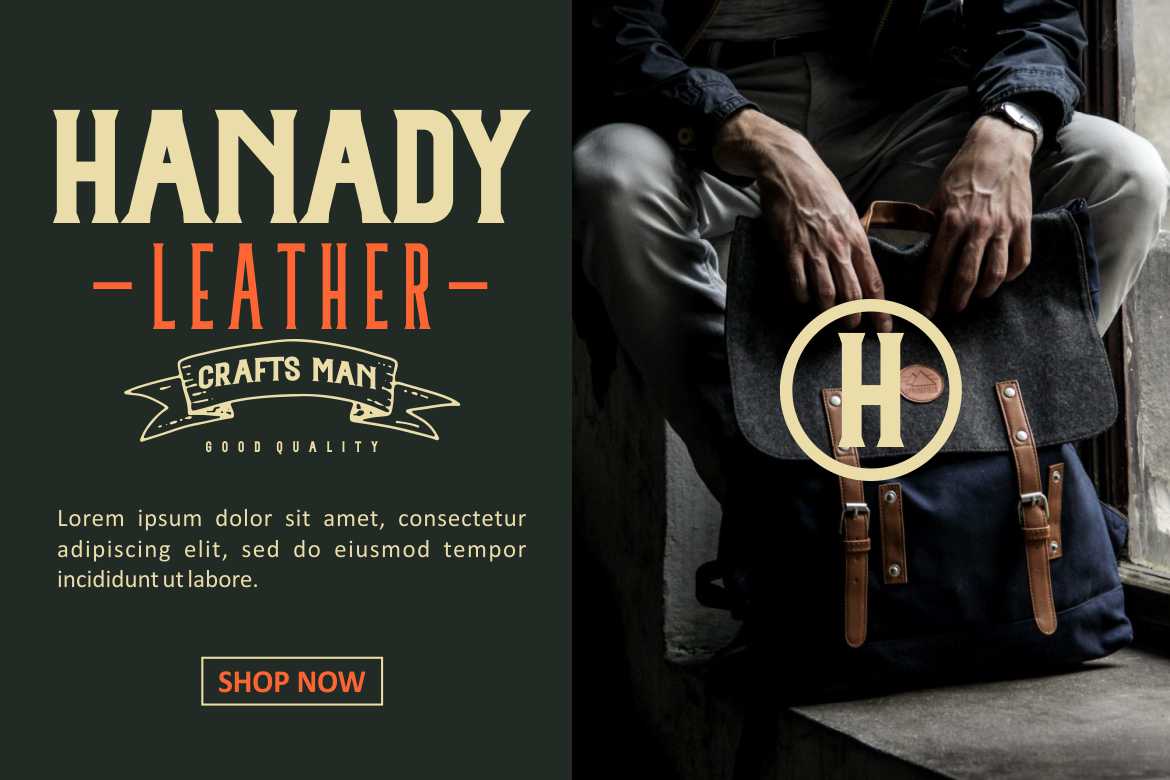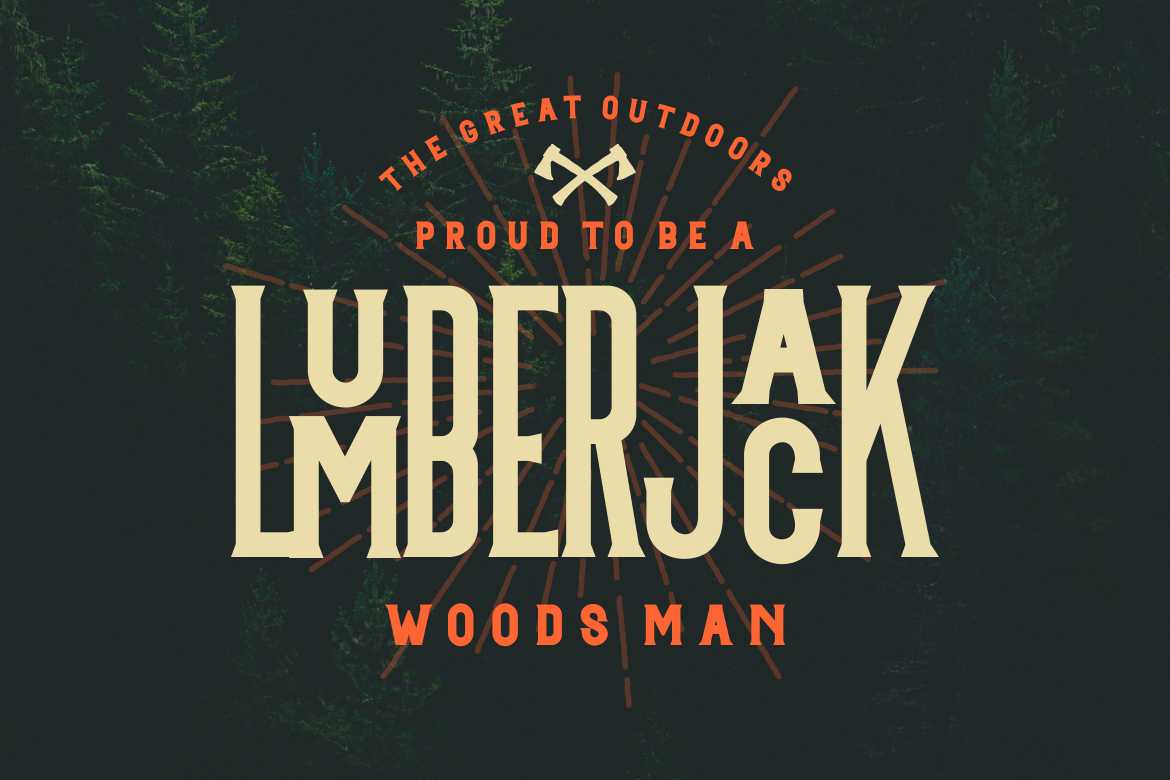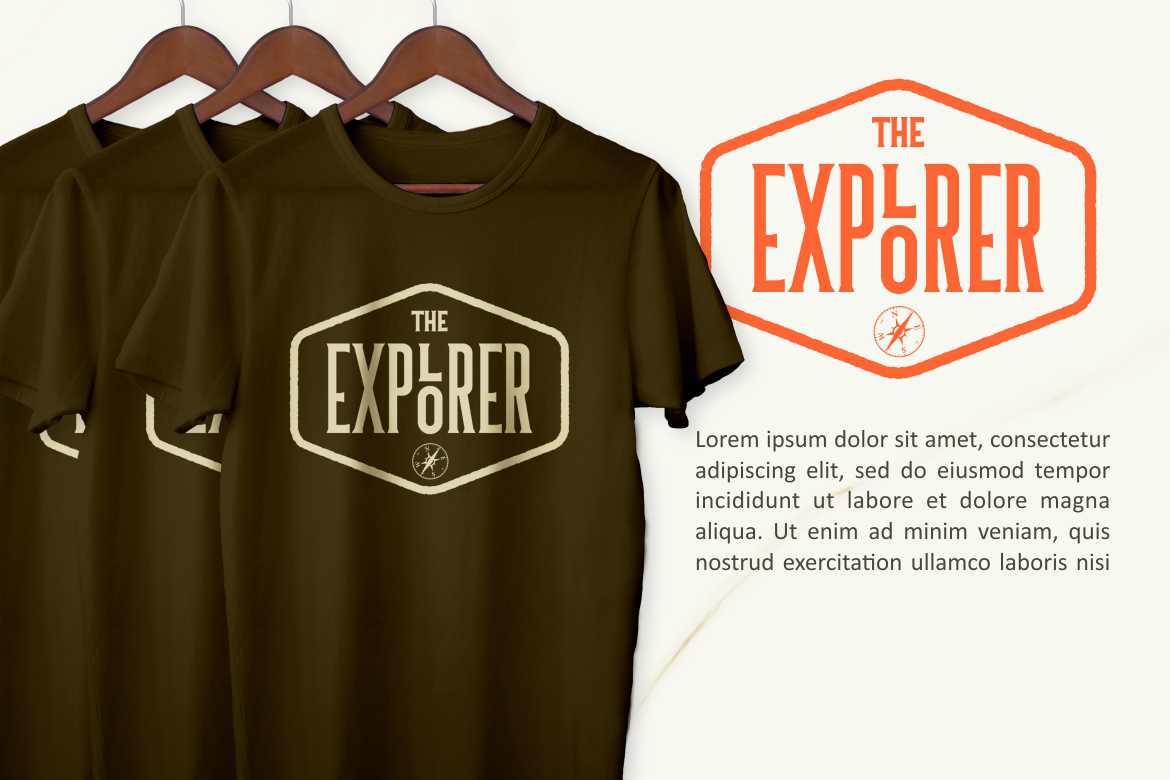
大多数人都喜欢使用Cleanyets SharpVintagestyle的BoldCap。这种字体组合非常适合您的许多设计项目。例如,Flyer,Logo Design,Badge,Packaging,Invitation等。也只支持标准的多语言Caps。大多数人都喜欢使用Cleanyets SharpVintagestyle的BoldCap。这种字体组合非常适合您的许多设计项目。如Flyer,Logo Design,Badge,Packaging,邀请和更多。也仅支持标准多语言。